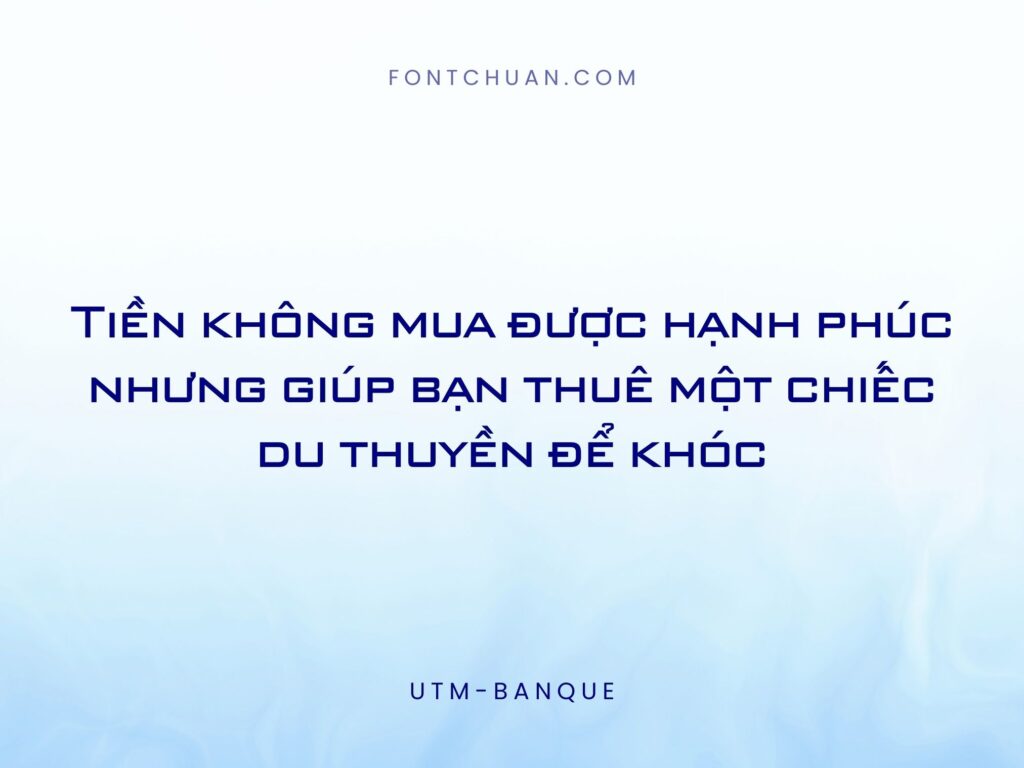
UTM Banque là một kiểu chữ sans-serif hiện đại với thiết kế rõ ràng, thanh thoát và tối giản. Các đường nét trong font được tạo dựng với độ dày đồng đều, cấu trúc hài hòa và nhấn mạnh tính chuyên nghiệp trong trình bày. Phiên bản Việt hóa do Đinh Kiên thực hiện, hỗ trợ đầy đủ tiếng Việt cùng hơn 100 ngôn ngữ khác. Font này đã được thành viên Font Chuẩn sưu tầm và chọn lọc để phục vụ cộng đồng thiết kế trong các dự án cần sự rõ ràng, thân thiện và hiện đại.
UTM Banque phù hợp với các thiết kế như tiêu đề, logo, giao diện web, tài liệu văn phòng, nhận diện thương hiệu hoặc hồ sơ năng lực. Các nét chữ sạch sẽ giúp font dễ dàng hiển thị trên nhiều chất liệu in ấn hoặc kỹ thuật số. Những ngành nghề như quảng cáo, giáo dục, công nghệ và bất động sản hoàn toàn có thể ứng dụng UTM Banque để tạo cảm giác đáng tin cậy và hiện đại trong thiết kế.